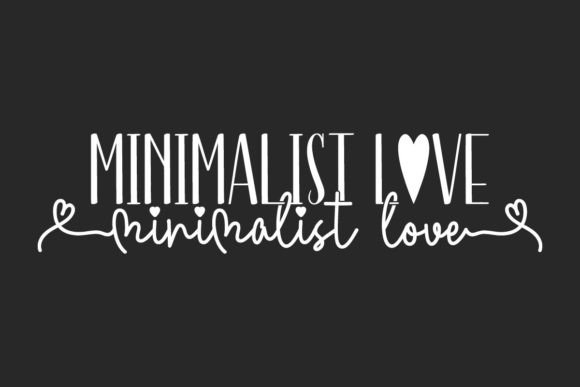
Minimalist Love
適切なデザイン要素を見つけるのは難しい場合がありますが、Minimalist Loveは作品を即座に引き立てる優れたコレクションを提供します。
精密に作られたMinimalist Loveは、クリーンなベクター、滑らかなタイポグラフィ、そして安心のための商用ライセンスを提供します。
POD(オンデマンド印刷)製品、結婚式の招待状、またはソーシャルメディアのグラフィックを作成している場合でも、Minimalist Loveは理想的です。